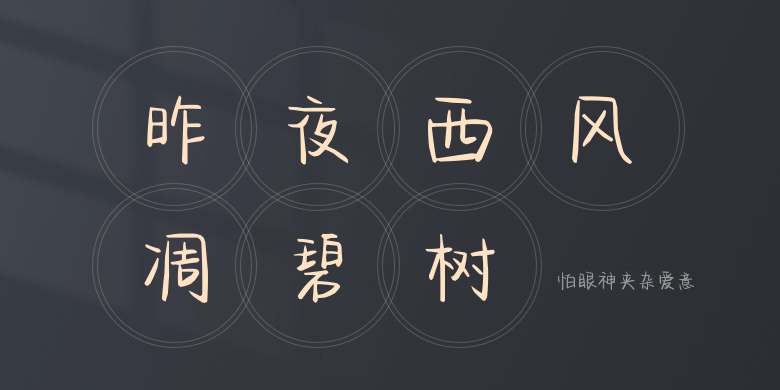
怕眼神夹杂爱意
怕眼神夹杂爱意,这款字体结构工整、笔画清晰,兼顾美观与易读性,适用于标题、正文、海报、包装、LOGO 等多种场景。字形优雅稳定,风格百搭耐看,适配日常排版与创意设计,让文字呈现更舒适、更具质感。怕眼神夹杂爱意一笔一画,皆是细节,以均衡的比例、流畅的线条打造舒适视觉体验,字形端正大气,风格简约现代。无论是商业设计、品牌宣传还是日常排版,都能轻松驾驭,让文字更有格调与力量。怕眼神夹杂爱意字体下载。